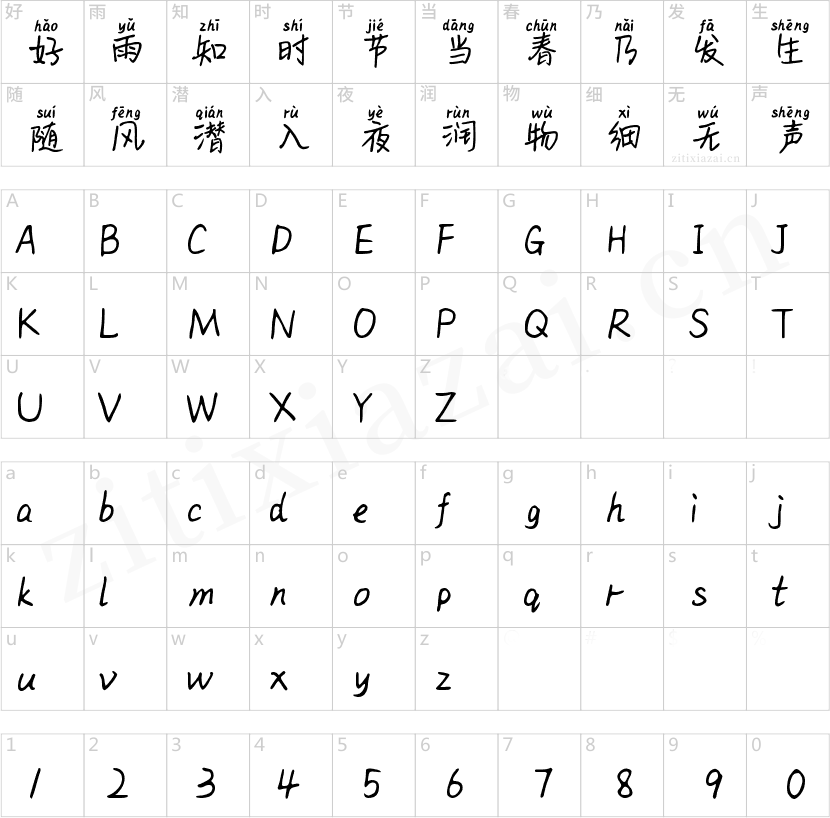
Aa笔尖华尔兹
Aa笔尖华尔兹字体
Aa笔尖华尔兹是一款非常具有艺术性的字体,它的设计灵感来源于对古典艺术的研究,同时又融入了现代字体设计的元素。字形优美,笔画粗细变化自然,给人以大气、典雅的感觉。Aa笔尖华尔兹是一款既传统又现代的字体,它的设计充满艺术感,美观大方,实用性也非常强。无论是对于设计师还是对于普通读者来说,都是一种非常不错的字体选择。Aa笔尖华尔兹适合用于具有艺术感的场合,比如海报、宣传单张、书籍封面等。由于其字形流畅且具有动态感,也适合用于大量的文本排版,如报纸、杂志等。